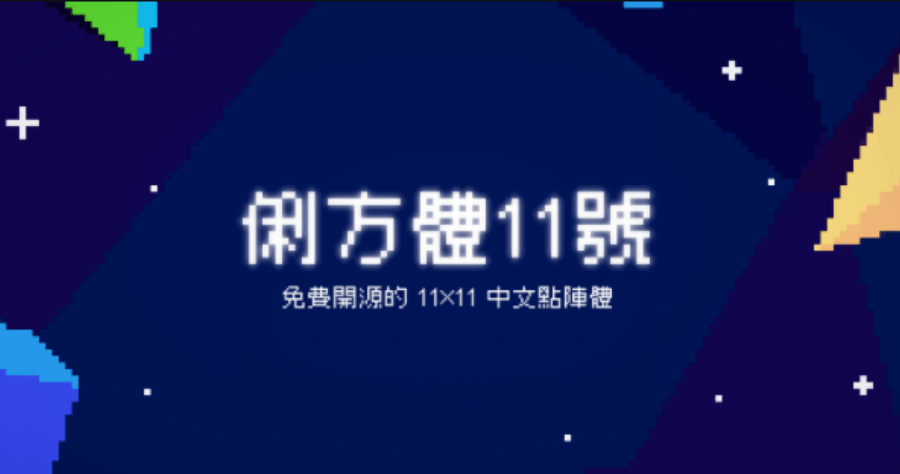
最近像素風格的美術、畫作、遊戲相當紅,有沒有推薦的「像素字體」呢?最近小編發現「俐方體 11 號」Cubic 11 免費中文點陣體,是基於 M⁺ gothic 12r 衍生的開源繁體中文點陣字型,開放給大家免費下載使用,基於 SIL Open Font License 1.1 授權條款公開發布,因此任何人可以無償使用此字型,包含商用,無須告知原作者,非常推薦大家把此款字型收下唷。另外也有其它風格的點陣字體,像是 じゃっき 點陣字體像素感又更強烈一些。
俐方體 11 號是以日文字型 M⁺ gothic 12r 為基礎替繁體中文進行修改與擴充,其中包括適用繁體中文的標點符號以及較符合臺灣習慣的字形等。
俐方體 11 號